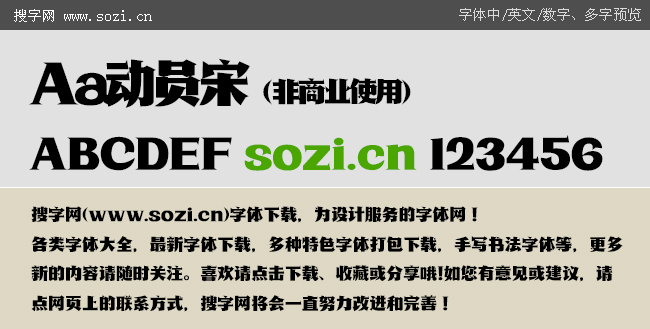
Aa動(dòng)員宋
搜字網(wǎng)給大家提供一款A(yù)a動(dòng)員宋(非商業(yè)使用)中文字體下載,Aa動(dòng)員宋是一款藝術(shù)宋體字體,該字體筆觸粗實(shí)厚重,字形端正大方,非常醒目。適合應(yīng)用于藝術(shù)設(shè)計(jì)、平面宣傳設(shè)計(jì)、網(wǎng)頁設(shè)計(jì)、海報(bào)設(shè)計(jì)等應(yīng)用(此字體為個(gè)人非商用版,商用可以聯(lián)系QQ:1006760504)。